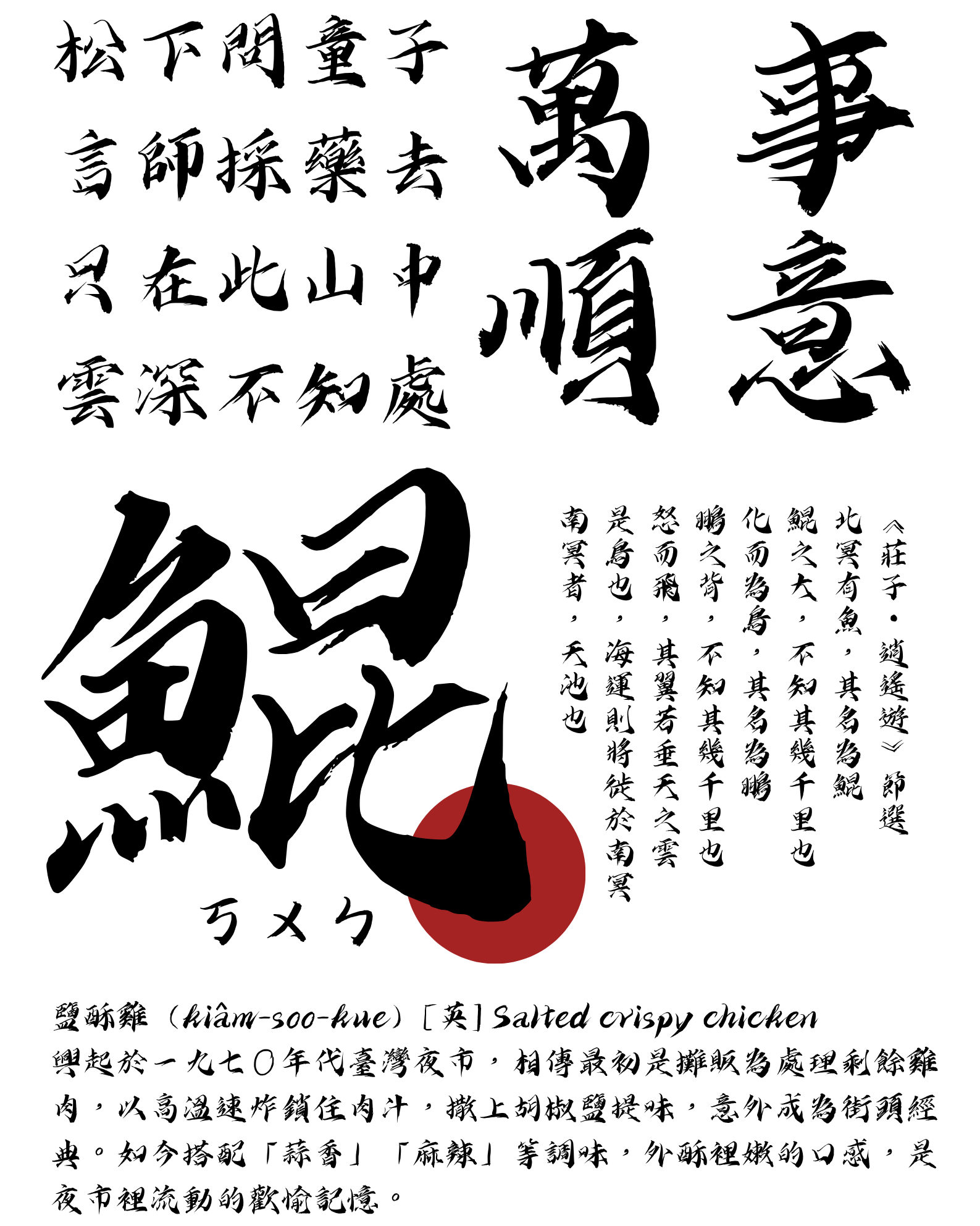
字嶼雲遊手書
字嶼雲遊手書 / Fontprime 簡介
- 「字嶼雲遊手書」整體字勢開合揖讓得宜,騰挪轉折間,不致過於纖秀婉約,婉轉中猶見鏗鏘力道,鋒芒盡顯。透過局部形變與筆勢外拓,疊加出整體氣勢,兼顧陰柔與陽剛、含蓄與強勁之美。露鋒用筆貫穿字體始終,結體緊緻,大量曲線更強化字勢動感與字形張力,恰似流雲縈繞劍鋒,飄逸中蘊藏銳勁 。
標準字集:自由創作,靈活應用
字嶼雲遊手書以臺灣常用標准字集為標准,參考jf7000字集,包括注音符號、英文字母、阿拉伯數字和標點符號,約7640字以上。涵蓋了日常生活和設計中常用的漢字、字母、數字以及各類標點符號,支援大多數使用情境。
無論是面向大眾的設計作品,還是涉及到國際交流、英文元素的設計專案,字嶼雲遊手書 都能提供支援。(目前字集先以臺灣常用標準字為基礎建置,後續會逐步規劃擴充在地化用字,期待未來能更完整地服務書寫需求。)在處理英文單詞或數字信息時,其字母和數字的設計與漢字相互呼應,保證了整體排版的和諧統一。讓設計師在創作過程中可以更加專注於發揮創意,靈活地運用這款字體打造出各種獨具匠心的作品。
我們希望這款字有無限的可能性:
- 國潮文創:手帳封面題字、刺繡吊飾文字
- 茶飲與伴手禮:珍珠奶茶杯身題字、鳳梨酥禮盒側邊文案
- 出版領域:鄉土神話故事集、山林散文選的封面與章節標題
- 影視動畫:仙俠劇開場片名、廟宇場景牌匾題字
- 戶外廣告:古蹟園區導覽牌、文創商圈燈箱
- 傳統服飾:廟會常見的服飾刺繡文字、改良旗袍腰帶印字
- 文博展覽:特展海報、老街文物說明卡
- 品牌識別:中藥行招牌、台式茶館
- 工藝飾品:陶瓷茶具底款、珊瑚吊墜刻字
字嶼雲遊手書
這是一款以毛筆字風格為基底,更為強調字體筆畫的曲折收放變化的創意手書。